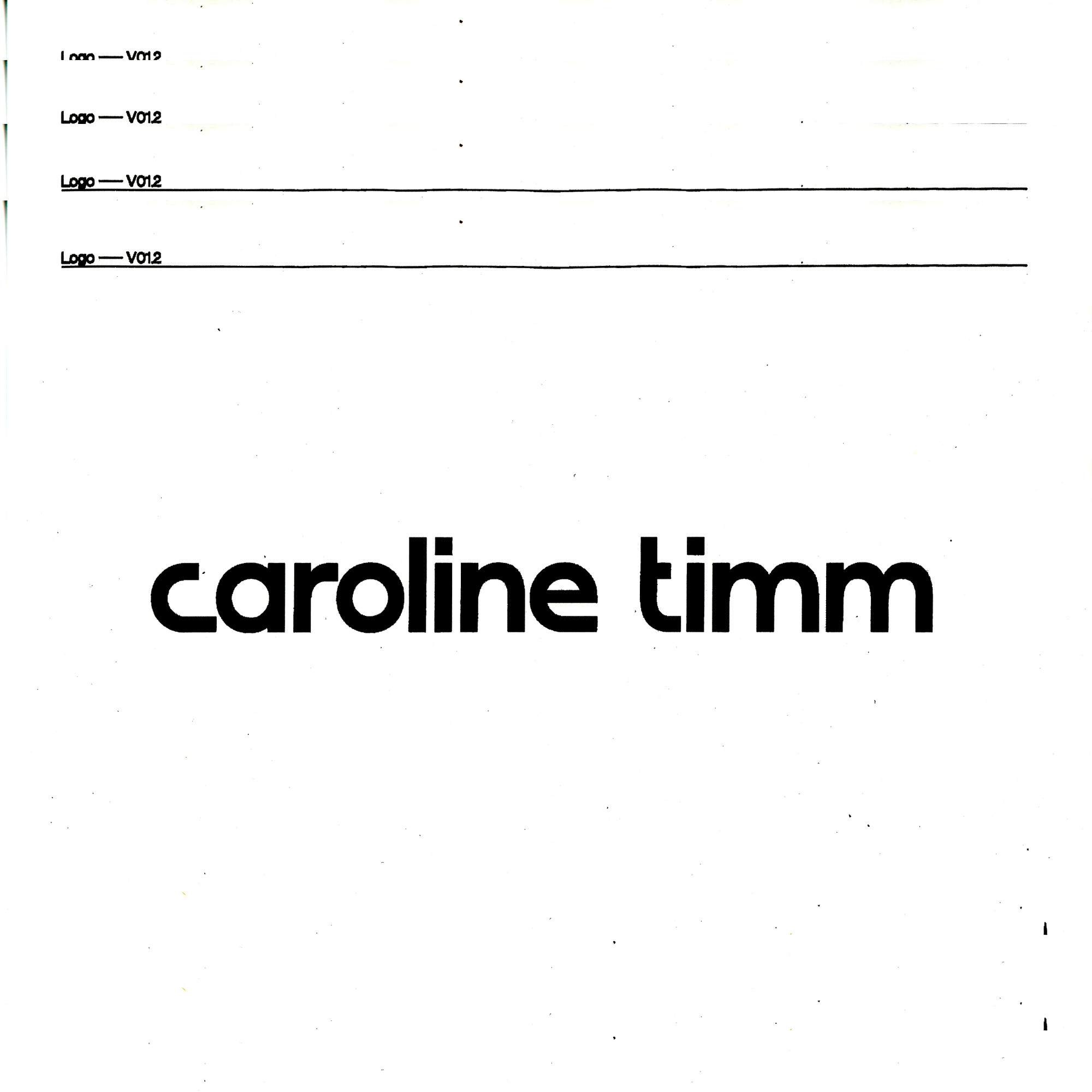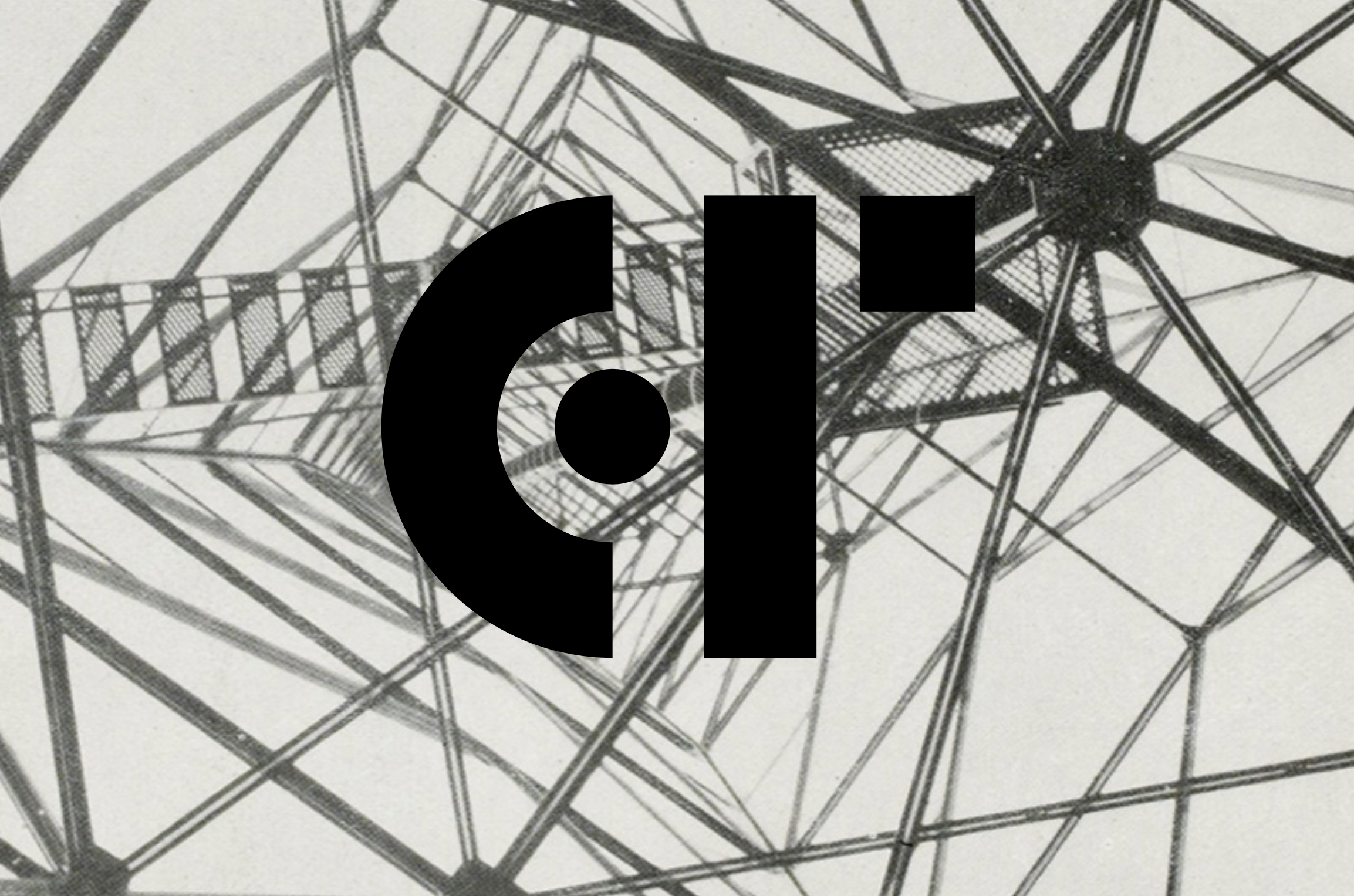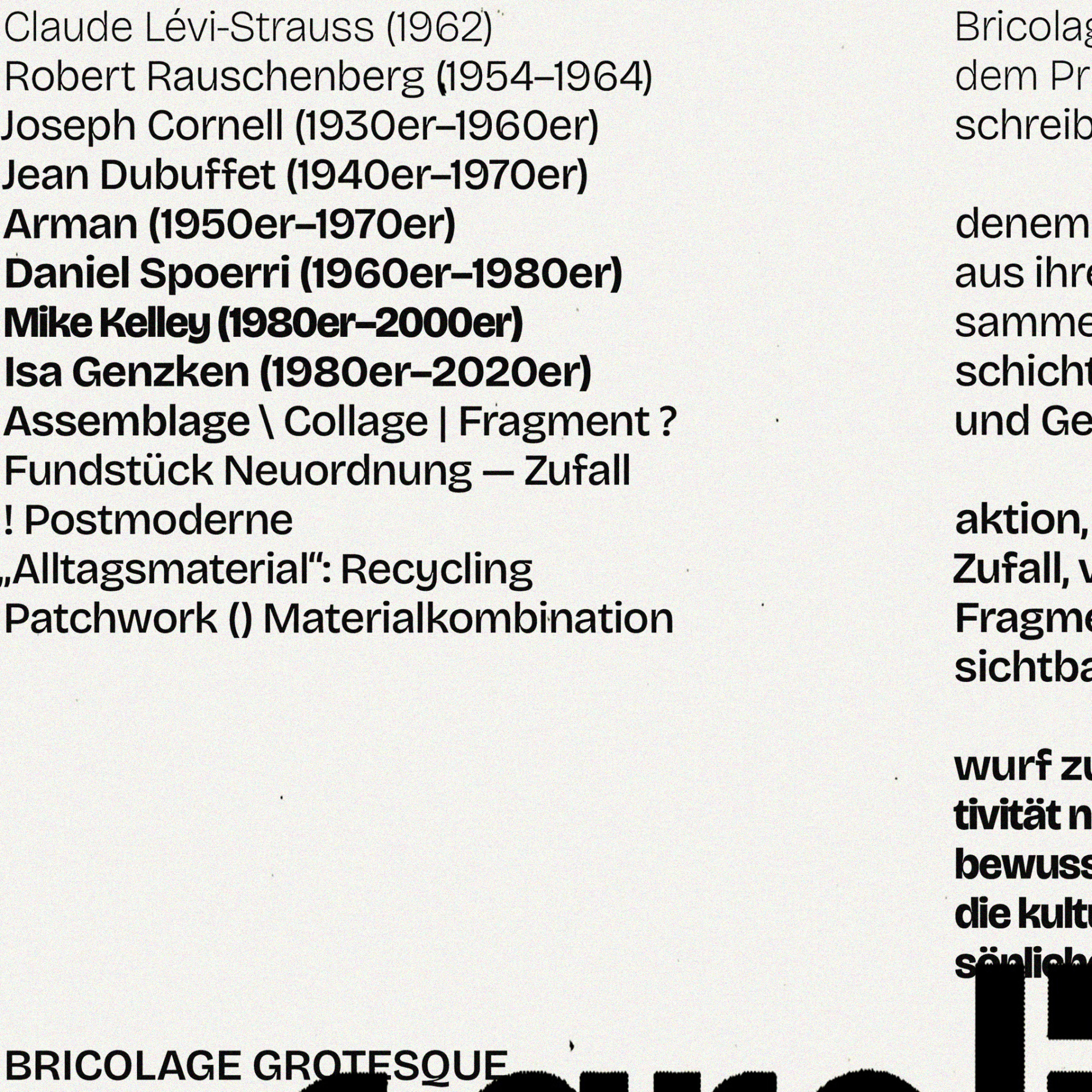
Caroline Timm
Caroline Timm ist eine in Hamburg lebende Künstlerin, die vor allem mit Keramik und Malerei arbeitet. In ihrer künstlerischen Praxis untersucht sie die Beziehung zwischen Architektur, Material und Erinnerung – geprägt von ihrem Hintergrund in der Stadtplanung sowie ihrem langjährigen Interesse an der Atmosphäre gebauter Räume.
Aus dieser Auseinandersetzung mit Architektur und Materialität entstand ein visuelles Erscheinungsbild, das genau diese atmosphärische Qualität aufgreift. Neben einem geometrischen, an das Bauhaus erinnernden Logo wurde eine reichhaltige, naturnahe Farbwelt entwickelt. Als Hausschrift fiel die Wahl auf die Bricolage Grotesque die eine weiche, kontrastreichen aber klare Haltung vermittelt.
Schrift: Bricolage Grotesque von Mathieu Triay